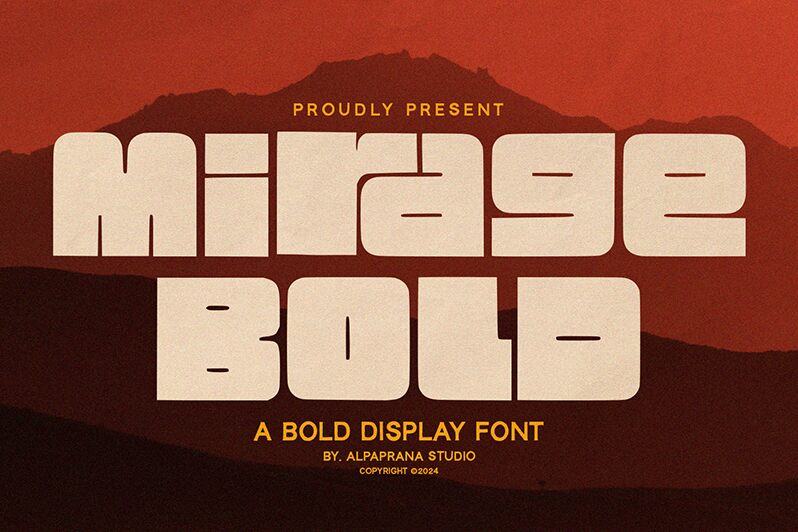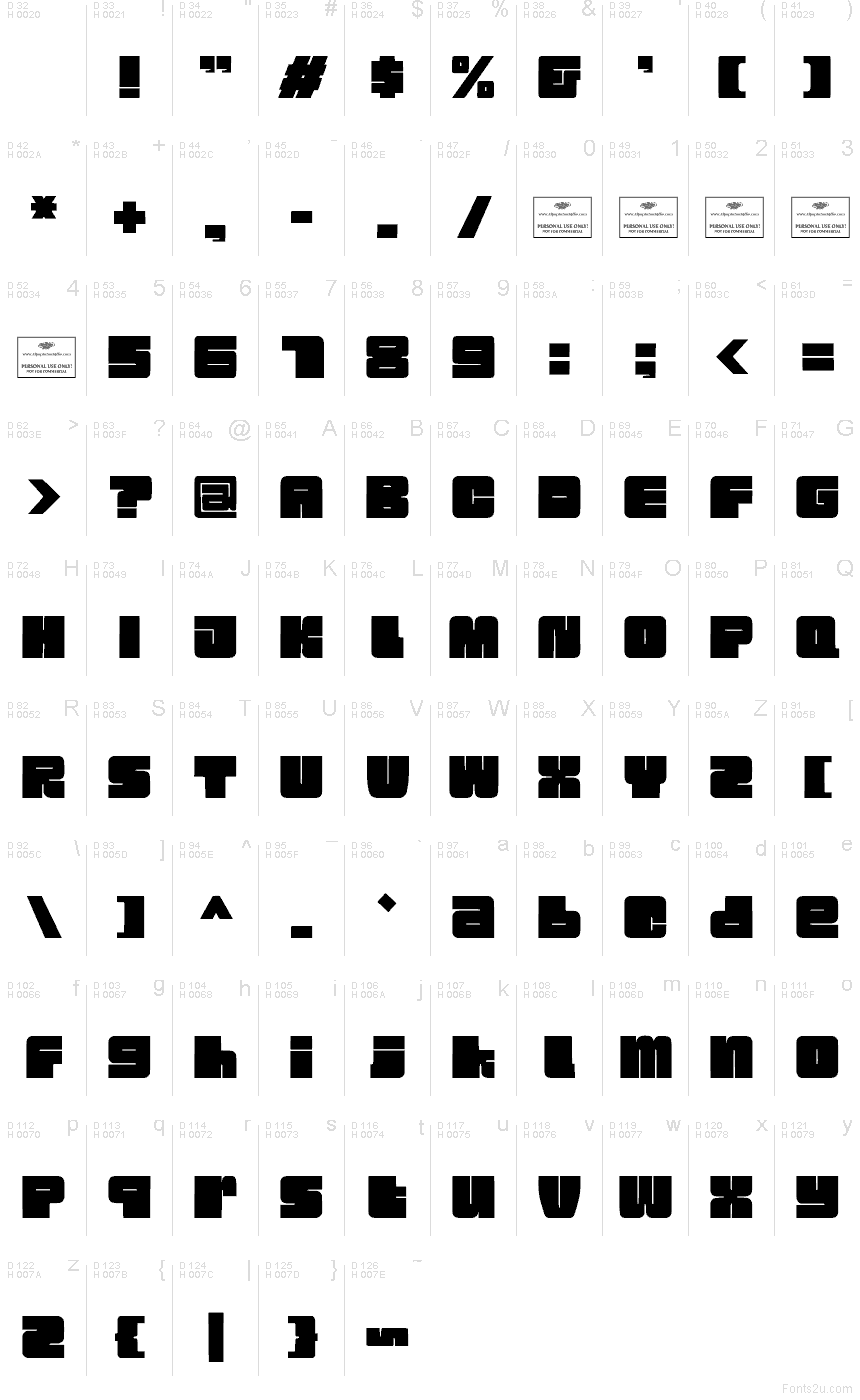
Il font Mirage Bold di Alpaprana Studio conferisce alla famiglia Mirage un carattere massiccio e futuristico, con angoli smussati e intagli netti che rendono ogni parola quasi progettata meccanicamente. È un font sans serif decorativo di tipo techno, gratuito, che ricorda la segnaletica in plastica stampata: audace, compatto e geometricamente deciso, senza risultare mai freddo.
Utilizzando Mirage Bold, otterrai risultati d'impatto su titoli di videogiochi, poster sci-fi, branding e-sport, copertine di album, volantini, gadget tecnologici e titoli accattivanti per i social. Impostalo in dimensioni grandi per far risaltare le incisioni e abbinalo a un sans serif neutro (o un grottesco semplice) per il testo principale: questo font gratuito farà tutto il lavoro pesante nelle tue intestazioni.